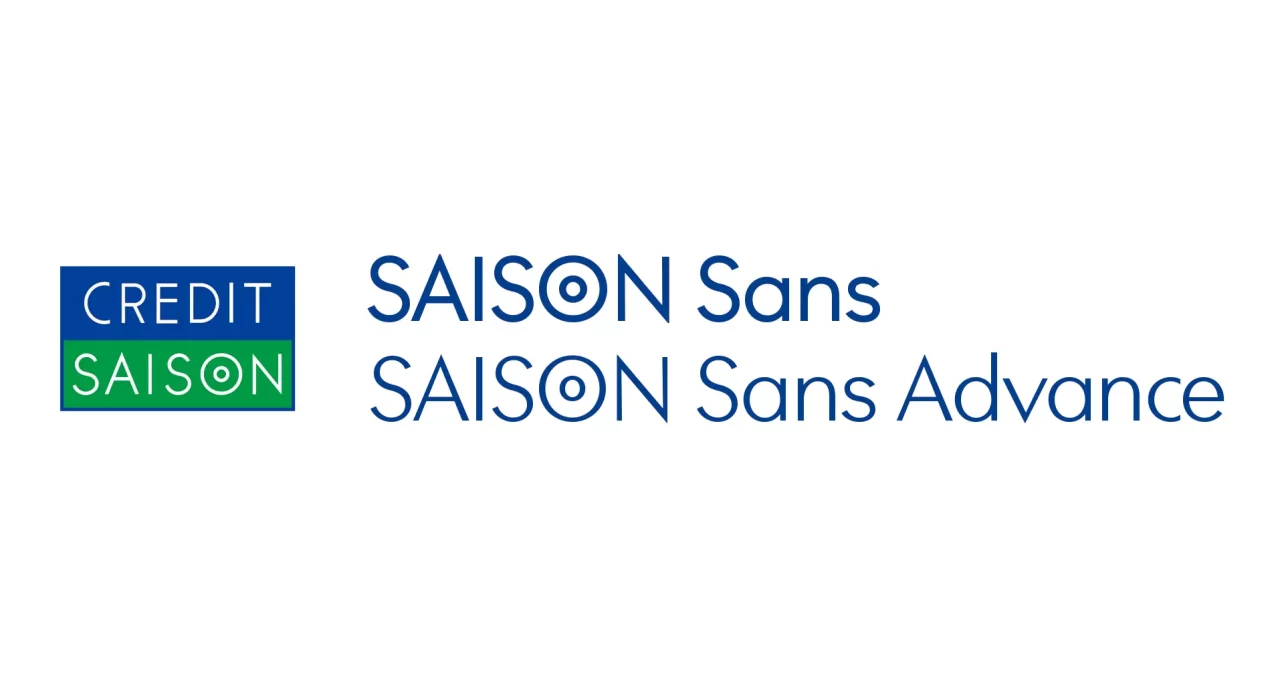
1983年から「セゾンカード」で知られている株式会社クレディセゾン(以下、クレディセゾン)は、2030年に向けた目指す姿として「GLOBAL NEO FINANCE COMPANY ~金融をコアとしたグローバルな総合生活サービスグループ~」を掲げ、私たちの生活に広くアプローチする事業を展開しています。
クレディセゾンでは、日本のグラフィックデザインを牽引してきた田中一光氏によって制作されたロゴタイプが、今日までブランドの象徴として受け継がれています。グローバルな事業展開が急速に進むなか、クレディセゾンのブランドイメージに一貫性を持たせるために、この歴史あるロゴタイプを踏襲した欧文書体の開発プロジェクトが発足。
クレディセゾンとフォントワークス書体デザインディレクター ヨアヒム・ミュラー・ランセイらが率いるチームによって制作した「SAISON Sans(セゾン サンズ)」および「SAISON Sans Advance(セゾン サンズ アドバンス)」2つのコーポレートフォントが完成しました。
1. SAISON Sans:歴史あるクレディセゾンのロゴタイプを継承する書体
SAISON Sansは、セゾンカードのロゴでもなじみがある、既存のロゴタイプを踏襲したジオメトリック(幾何学的な)サンセリフ体です。フォントワークスの書体デザインディレクターのヨアヒムはこのロゴタイプを「幾何学的かつ型破りなデザインだからこそ、目を引き、愛されてきたのではないか」と語ります。これをヨアヒムはクレディセゾンらしさと捉え、書体へと落とし込んでいきました。
ヨアヒムははじめに、既存のロゴタイプの詳細な分析を行い、全文字のプロポーションの見直しを開始。Mなどの尖ったオーバーシュート※をわずかに面取りする、視覚的な錯覚を考慮に入れた微調整を実施する、アウトラインをなめらかにするなどデザインを施しました。
これにより、クレディセゾンらしさが溢れるコーポレートフォントが完成。社内外への発信に向けたさまざなシーンで利用が可能となりました。
※オーバーシュート:書体が一貫した視覚的高さを保つために、一部が基準線や中心ラインをわずかにはみ出す現象のこと
2.SAISON Sans Advance:クレディセゾンの文化を未来へつなぐ。伝統と先進性を備えた書体
SAISON Sansよりさらに可読性を追及し完成した書体が、SAISON Sans Advanceです。均一なストロークで構成されるSAISON Sansのアドバンス版として、コントラストの要素を加えました。線画の太さにわずかな変化を加えることで、カリグラフィの要素を取り入れつつ自然な抑揚を表現します。これにより文章にエレガントで洗練された印象を与え、欧文の長文を組版する際には、読みやすさを一層引き立たせます。
田中一光氏のデザインアイデンティティが引き継がれるオルタネート(異体字)
SAISON Sans/Advanceの両方において、クレディセゾンのロゴタイプで象徴的な存在となっている二重丸の「O(オー)」のオルタネート(異体字)も用意されています。田中一光氏のデザインアイデンティティは、この書体にもしっかりと継承されました。今後SAISON Sans/Advanceは、クレディセゾンの社内外でのコミュニケーションにおいて、一貫性のあるブランドイメージを構築するため、公式資料やホームページ、IRサイトなど、デジタルメディア全体にわたって使用される予定です。
日本タイポグラフィ年鑑2025 タイプデザイン部門 入選
日本タイポグラフィ年鑑とは、NPO法人 日本タイポグラフィ協会が主催している海外からも高い評価を受けているアワードです。この度「日本タイポグラフィ年鑑2025」において、SAISON Sans/Advanceが国内外の2045点の応募の中からタイプデザイン部門に入選しました。
株式会社クレディセゾン ブランディング戦略部 課長/リードデザイナー 山本尚毅氏コメント
当社は、商品を売るのではなく、ライフスタイルを提案するという姿勢を根底に持っておりますが、そのために必要なのは皆さまとの対話です。文字はコミュニケーションを支える重要な要素であり、書体の印象は意識しなくとも受け手に確実に伝わります。誠実な文字、楽しそうな文字、遊び心のある文字、そういった意味でSAISON Sansはクレディセゾンらしい文字となりました。現在はまだ、クレディセゾンのアイデンティティを時代に合わせ整理した段階に過ぎません。グループ全体やグローバルも含めて一体になり、コーポレートフォントを通じて、当社の取り組みやブランドの変化が一貫して視覚的に伝わり、社内にも、生活者の皆さまにも、これまで以上に深いコミュニケーションが広がっていくことをこれからも目指していきます。
フォントワークス株式会社 書体デザインディレクター ヨアヒム・ミュラー・ランセイ コメント
SAISON Sansの制作にあたり、常に私の頭の片隅には、クレディセゾンのロゴタイプをデザインした有名なデザイナー、田中一光氏がいました。ある意味、私が仕事をしているときに彼が私の肩越しに見守ってくれていたのかもしれません。田中氏のロゴの形は、幾何学的かつ型破りなデザインだからこそ、目を引き、愛されてきたのではないかと思います。しかし、この歴史あるロゴタイプを書体にするとなると、書体のニーズに合わせて文字の形状を調整し、読みやすさを際立たせる必要がありました。この書体が多くの人に魅力が伝わり、幅広いシーンで利用されることを願っています。